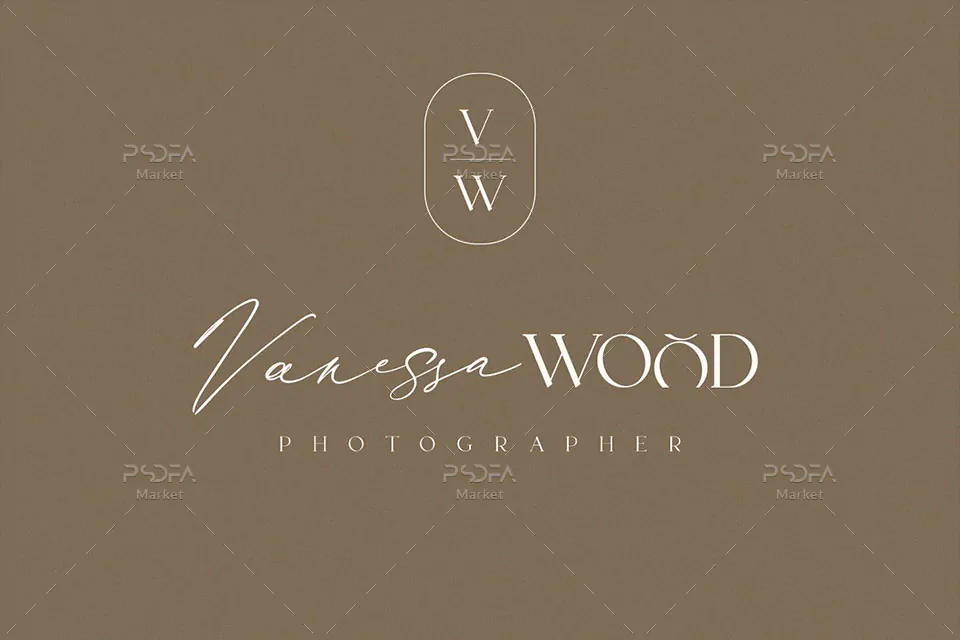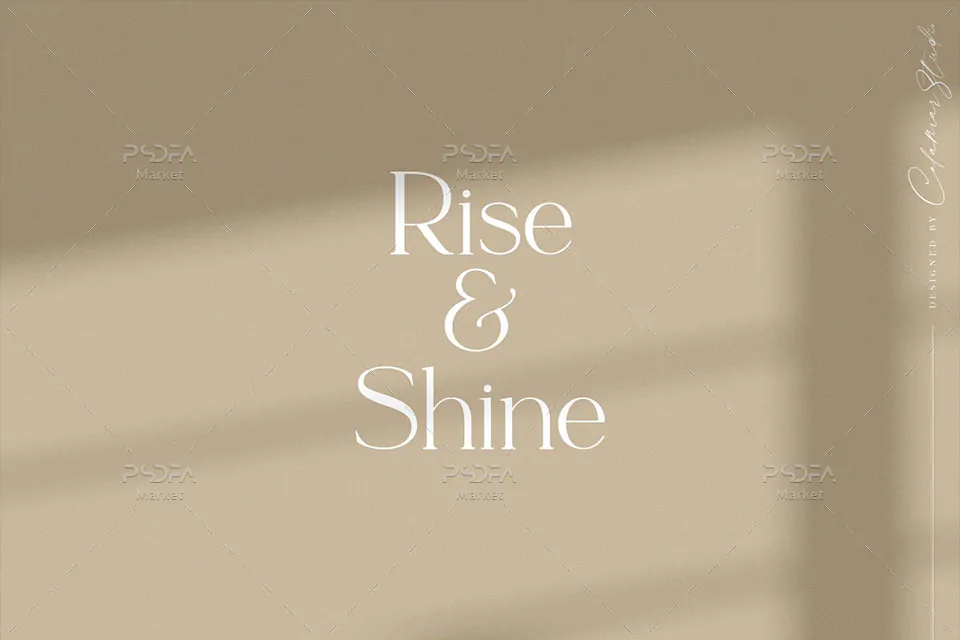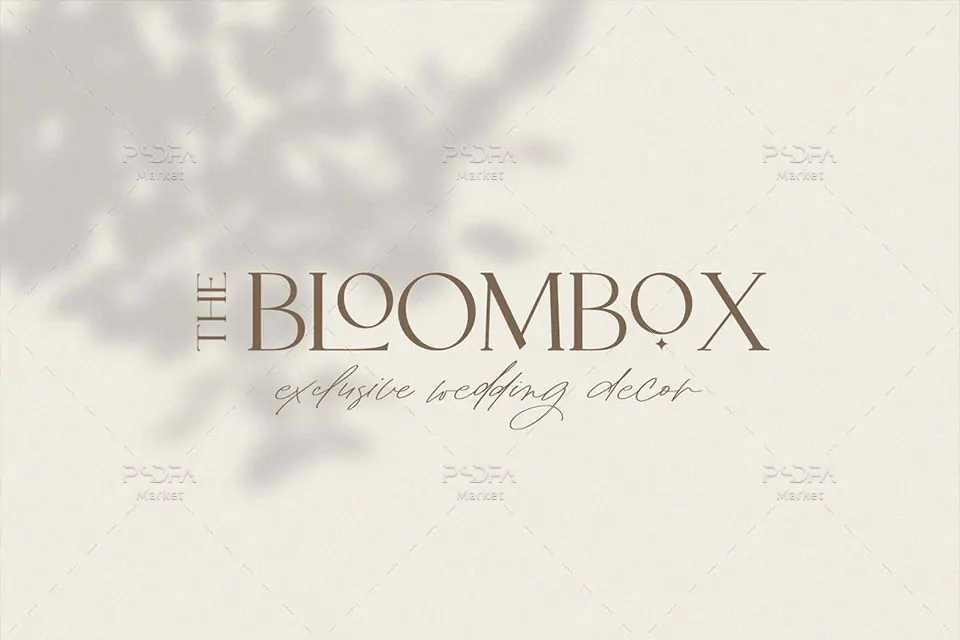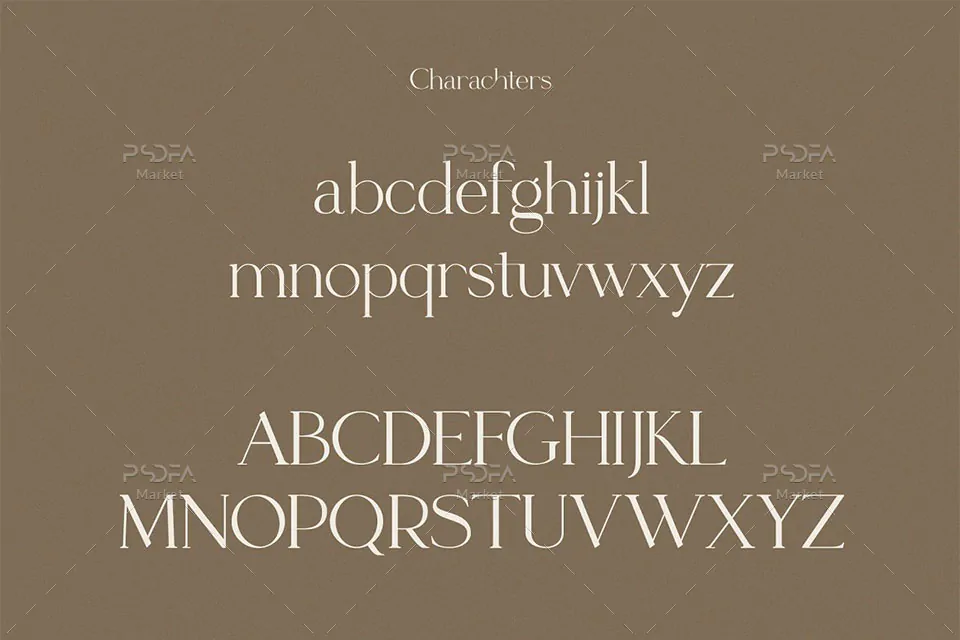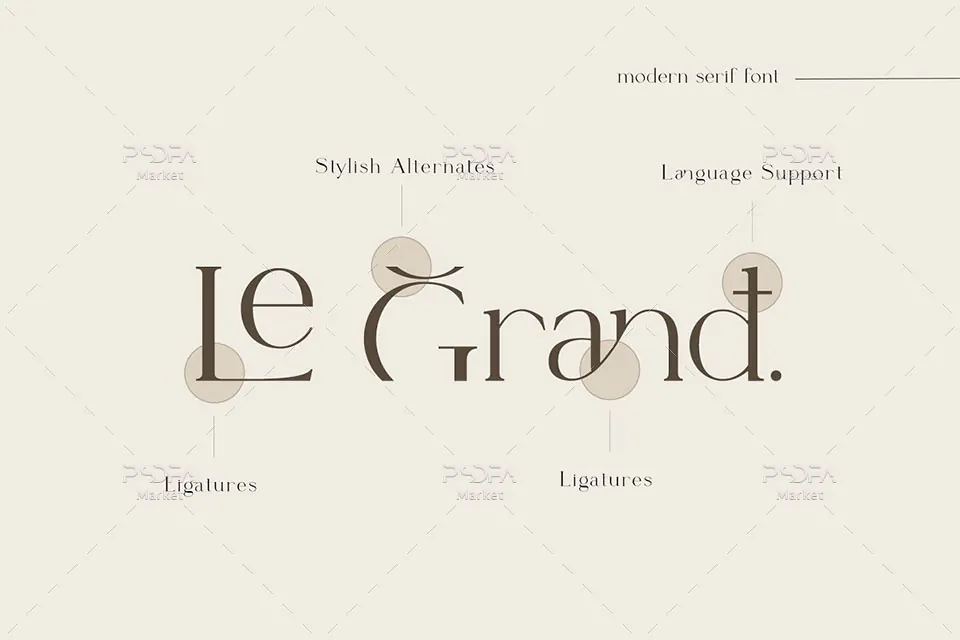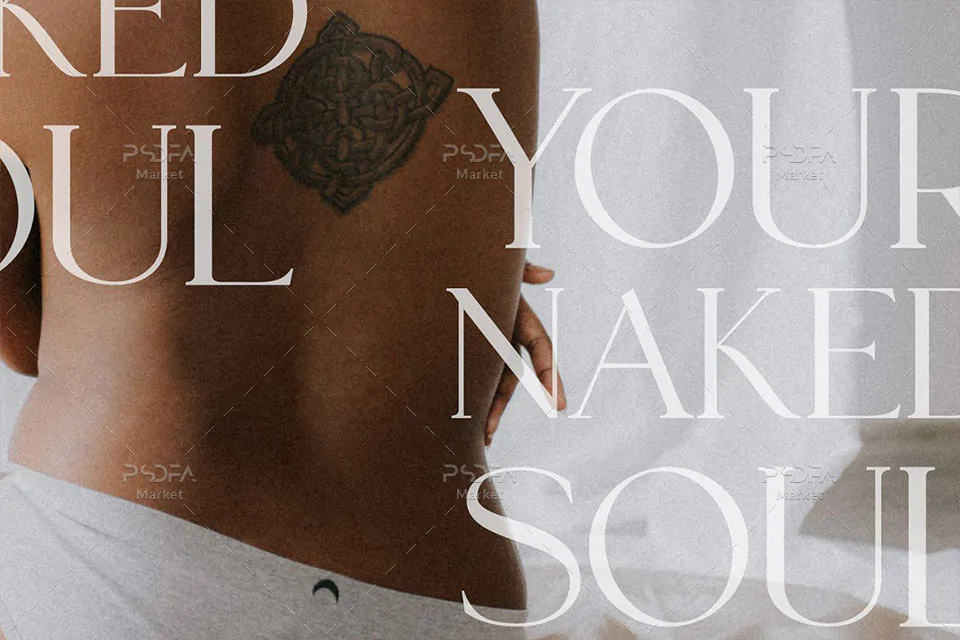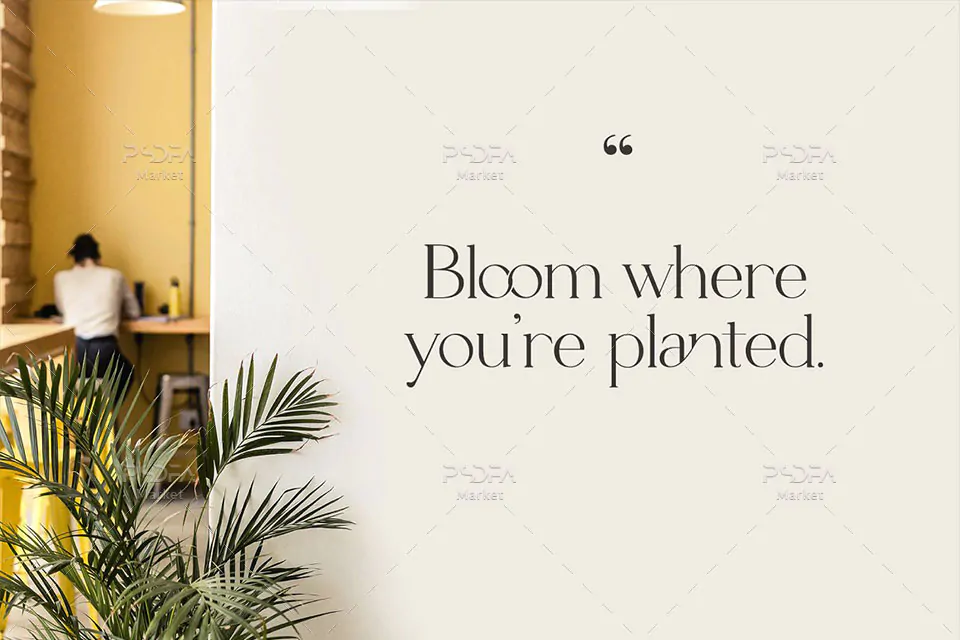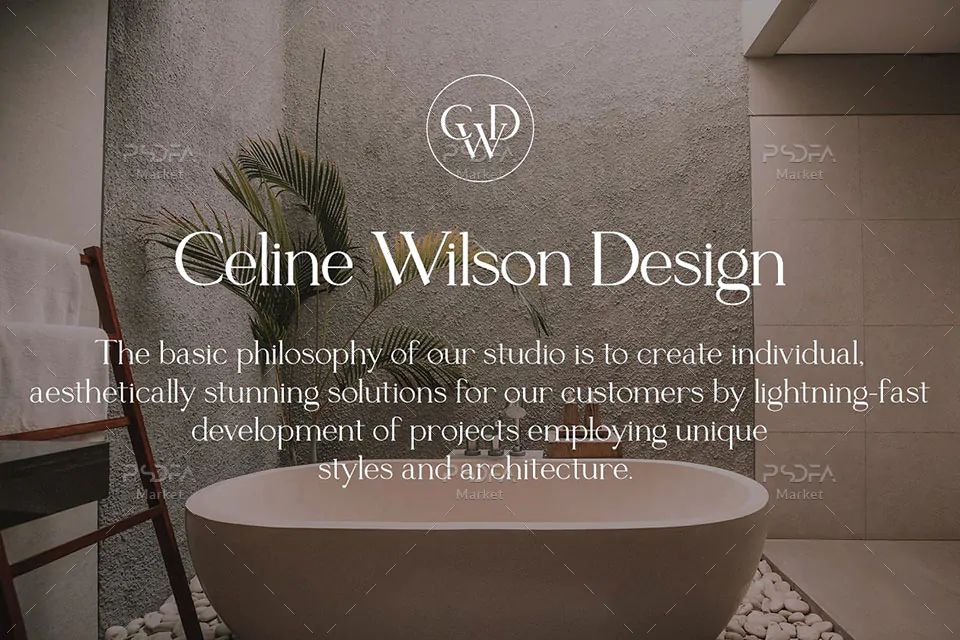
فونت انگلیسی سریف لیگاتور Le Grand مناسب برای طراحی
فونت انگلیسی سریف لیگاتور Le Grand
فونت انگلیسی سریف لیگاتور Le Grand یک قلم فوق العاده زیبا است که مناسب جهت استفاده در طرحهای گرافیکی مختلف به خصوص طراحی انواع لوگو و کارتهای مونوگرام میباشد. این فونت زیبا در 3 فرمت OTF, TTF, WOFF در فایل محصول قرار دارد که با نصب یکی از 2 فرمت ttf یا otf در پوشه فونتهای سیستم میتوانید از این فونت انگلیسی در تمام نرم افزارهای گرافیکی و تایپ متون همچون فتوشاپ، افتر افکت، پریمیر، ورد، پاورپوینت و … استفاده کنید.
فونت Le Grand در وزن معمولی (Regular) و در 4 حالت ضخیم، مورب، لیگاتور و کپیتال طراحی شده است که میتوانید از آن در طراحی انواع کارت تبریک، کارت پستال، کارت ویزیت، کارت عروسی، کارت دعوت، طراحی لوگو، کاور آلبوم موزیک، طراحی انواع بنر، پوستر، تراکت، تقویم و دیگر طرحهای گرافیکی استفاده کنید. از نسخه woff این قلم نیز میتوانید در طراحی صفحات وب استفاده کنید.
- وزن: Regular, Capital, Ligature, Bold, Italic